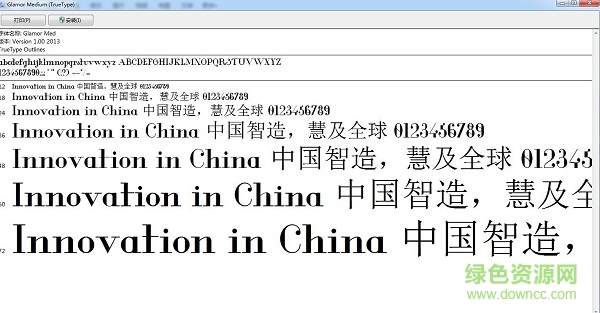
glamor字體是一款漂亮優(yōu)雅的時(shí)尚英文字體,非常適合女性設(shè)計(jì)主題,很多國(guó)際大牌的海報(bào)廣告以及時(shí)尚雜志封面都用過(guò)這款字體,喜歡的朋友快來(lái)綠色資源網(wǎng)下載吧!
經(jīng)典優(yōu)雅、充滿時(shí)尚大牌感,本字體由26歲的法國(guó)圖形設(shè)計(jì)師 Hendrick Rolandez 創(chuàng)作而成。